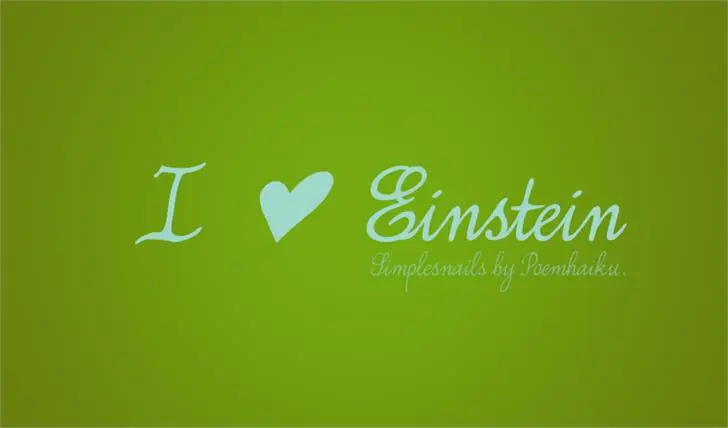
Simplesnails font – Download Grátis
Simplesnails é uma fonte iconográfica elegante e criativa que combina simetria, minimalismo e personalidade. Ela foi desenvolvida pelo designer Hamilton para atender aqueles que desejam adicionar um toque especial às suas criações digitais. A ideia por trás desta fonte é simplicidade pura, sem demoras ou excessos, mas com um toque de elegância e sutileza. Em uma era cada vez mais digitalizada, SImplesnails oferece uma maneira única de incorporar elementos iconográficos em designs, permitindo que sua marca brilhe de formas únicas e eficazes. Embora a fonte seja minimalista no design, ela é extremamente versátil. Pode ser utilizada para criar logotipos profissionais, identidades de marca ou até mesmo adicionar um toque de personalidade em mensagens digitais. Para designers que buscam algo além da fonte padrão, SImplesnails oferece uma maneira única de fazer suas criações singulares e memoráveis. Hamilton desenvolveu esta fonte com o objetivo de fornecer opções criativas para os designers. Eles buscaram incorporar os melhores elementos do design iconográfico em sua fonte, tornando-a não apenas uma ferramenta útil, mas também um elemento visual que pode dar vida a qualquer projeto digital. Em resumo, SImplesnails é mais do que uma fonte de simples simetria – é uma maneira de personalizar e humanizar o design digital em sua essência.